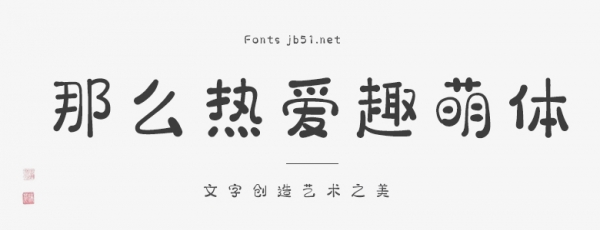
那么熱愛(ài)趣萌體是那么熱愛(ài)造字推出的一款萌趣藝術(shù)字體,該字體非常的可愛(ài)有趣,筆畫細(xì)節(jié)設(shè)計(jì)的十分細(xì)心,很有童趣創(chuàng)意,適用于包裝設(shè)計(jì)、電商、品牌名稱、漫畫、影視綜藝、游戲、各類商業(yè)海報(bào)、戶外廣告標(biāo)題等設(shè)計(jì)領(lǐng)域,歡迎喜歡此字體的朋友前來(lái)下載使用。